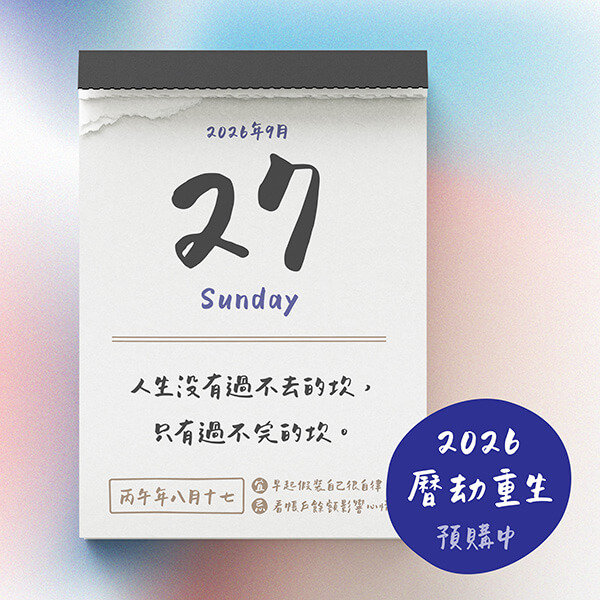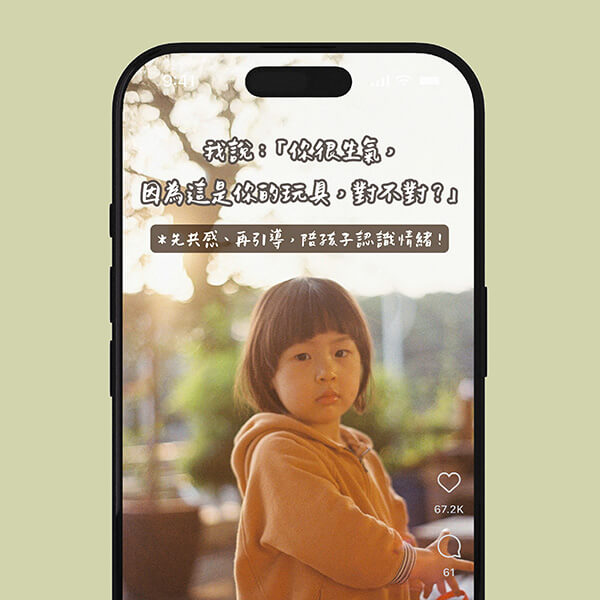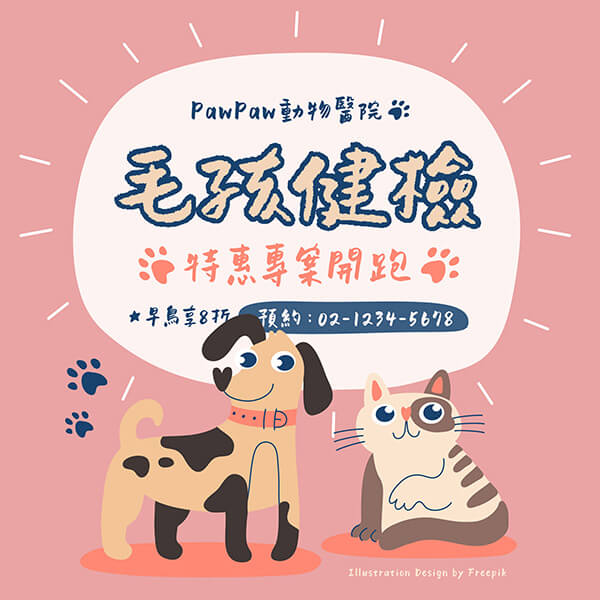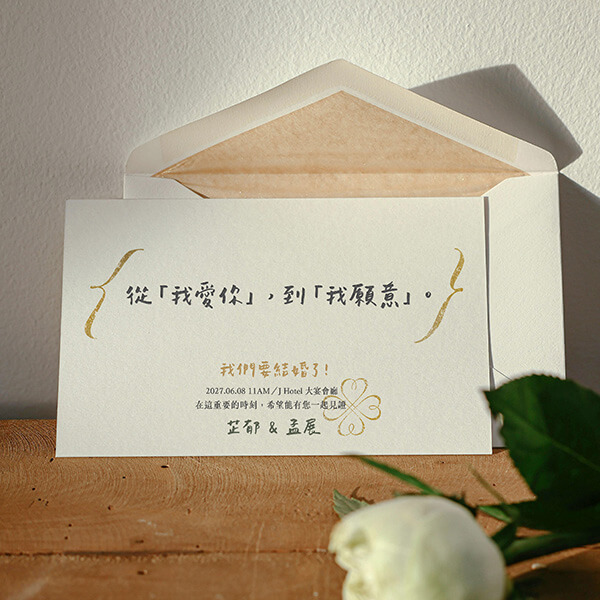
樂筆手寫體
溫暖可愛、活潑有彈性,能表達豐富情感
適用於設計、社群、影片與各樣生活場景中
帶來療癒且充滿想像的視覺體驗!
字型設計師
樂筆
2016年,以樂筆的身份在Instagram一個名為《日光實驗室》的帳號上分享手寫字圖文,起初從柔繪筆開始,透過軟筆頭的彈性,創作能表達豐富情感的粗細線條。希望在網路打字的世代,仍能傳遞手寫字的溫度,讓思想與意念在字體間流動,字游字在~縱然時間帶走了時間,仍深願手寫字能留住所有真摯情懷,以最質樸溫暖的方式說故事,讓美好全游向寬闊大海。